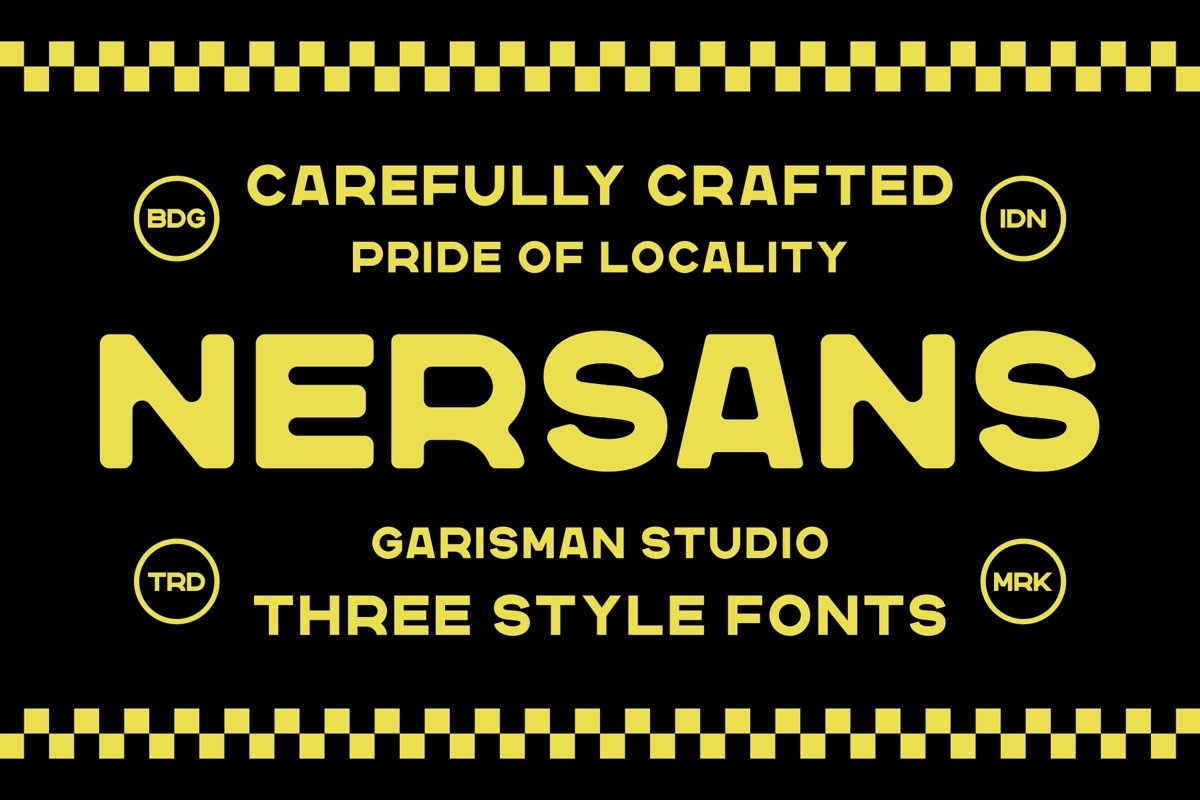
Nersans - Vintage Font with 3 Styles
Hadir dengan bangga: Nersans - Font Antik dengan 3 Gaya
Nersans lahir dari tampilan vintage yang menginspirasi dengan semua mesin terbang caps. Jenis huruf ini memberikan kesan vintage, klasik, tua, dan buatan tangan. Sudah PUA Encoded dan saya pikir font ini sangat cocok untuk orang yang mencari estetika vintage atau tipe logo. Cocok untuk segala desain grafis seperti bahan branding, t-shirt, cetak, kartu nama, logo, poster, t-shirt, fotografi, kutipan .etc.
• Gaya reguler dan miring
• Angka & Tanda Baca
• Karakter multibahasa (mendukung 16 bahasa): Afrika, Albania, Denmark, Belanda, Inggris, Estonia, Finlandia, Prancis, Jerman, Islandia, Italia, Norwegia, Portugis, Spanyol, Swedia, Zulu.